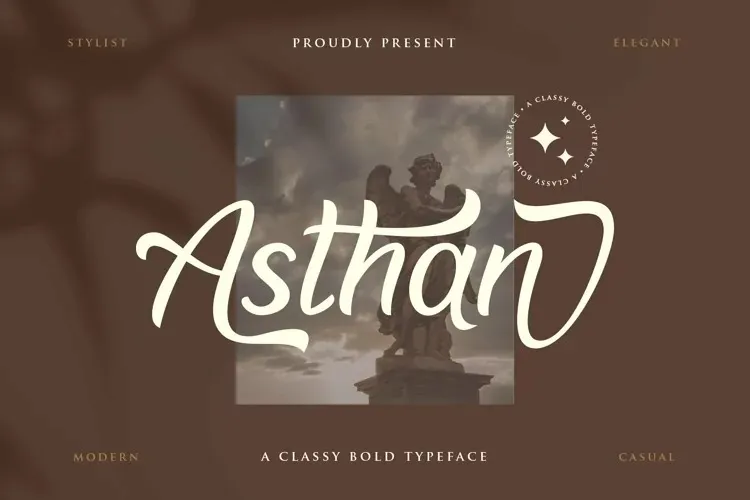
Asthana é uma linda fonte script moderna criada por Skillyas std. Perfeita para criações que exigem um toque único e autêntico, Asthana enriquece qualquer projeto de marca, design de casamento, postagem no mídia social, anúncios, embalagens de produtos, designs de produto, rótulos, fotografia, marca d’água, convites e material de estação criando um toque autêntico de escrita a mão. Seja para adicionar uma pitada feminina ou trendy em qualquer projeto gráfico, Asthana é sua font ideal. Este tipo de letra é perfeitamente adaptável a várias aplicações e manuseios, tornando-se perfeita para estilos variados e criativas do design. Engane-se se pensa que é apenas uma fonte, essa é um verdadeiro artista do design que adicionará um toque singular a qualquer projeto que ela reveste.